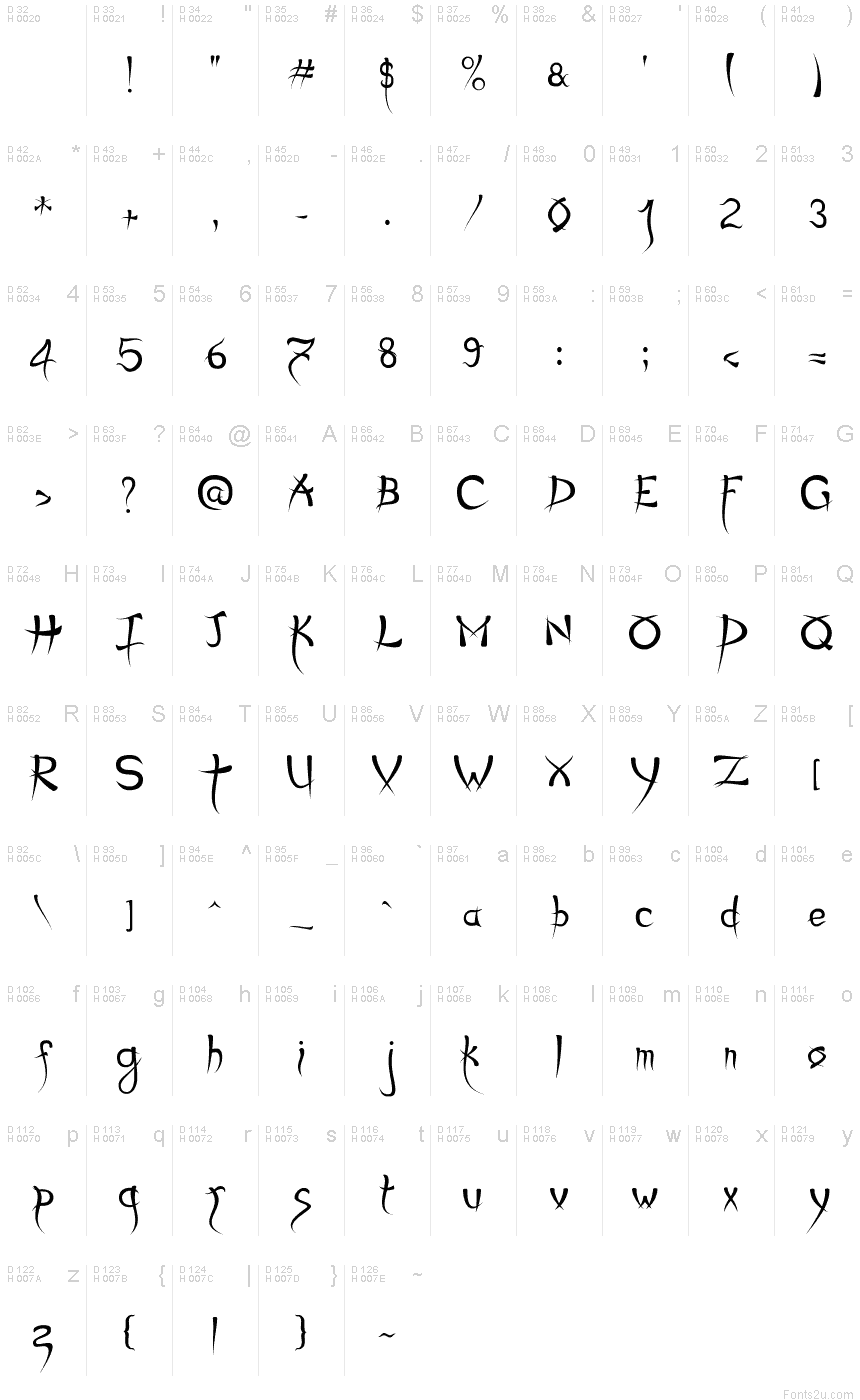
Psycho 字体
Psycho
Remy Demarest
Psycho 是一款极具吸引力的显示字体,散发出一种原始而坚定的强烈气息。由 Remy Demarest 设计,这款字体以其独特且锋利的几何美学脱颖而出,营造出一种难以捉摸的心理张力和令人不安的吸引力。其轻盈的字重在优雅与一种令人毛骨悚然的直观感之间取得了完美的平衡,使其成为恐怖主题品牌、电影海报或任何需要大胆且不妥协的视觉冲击力的排版设计的理想之选。
锐利、参差不齐的字形结构与戏剧性的衬线共同创造了独一无二的视觉签名,瞬间吸引目光并唤起一种阴森的氛围。"Psycho" 是一款用途广泛的字体,可以无缝衔接从醒目的标题到令人不寒而栗的正文,为任何旨在吸引并震慑受众的设计项目增添一抹不可忽视的锋芒。